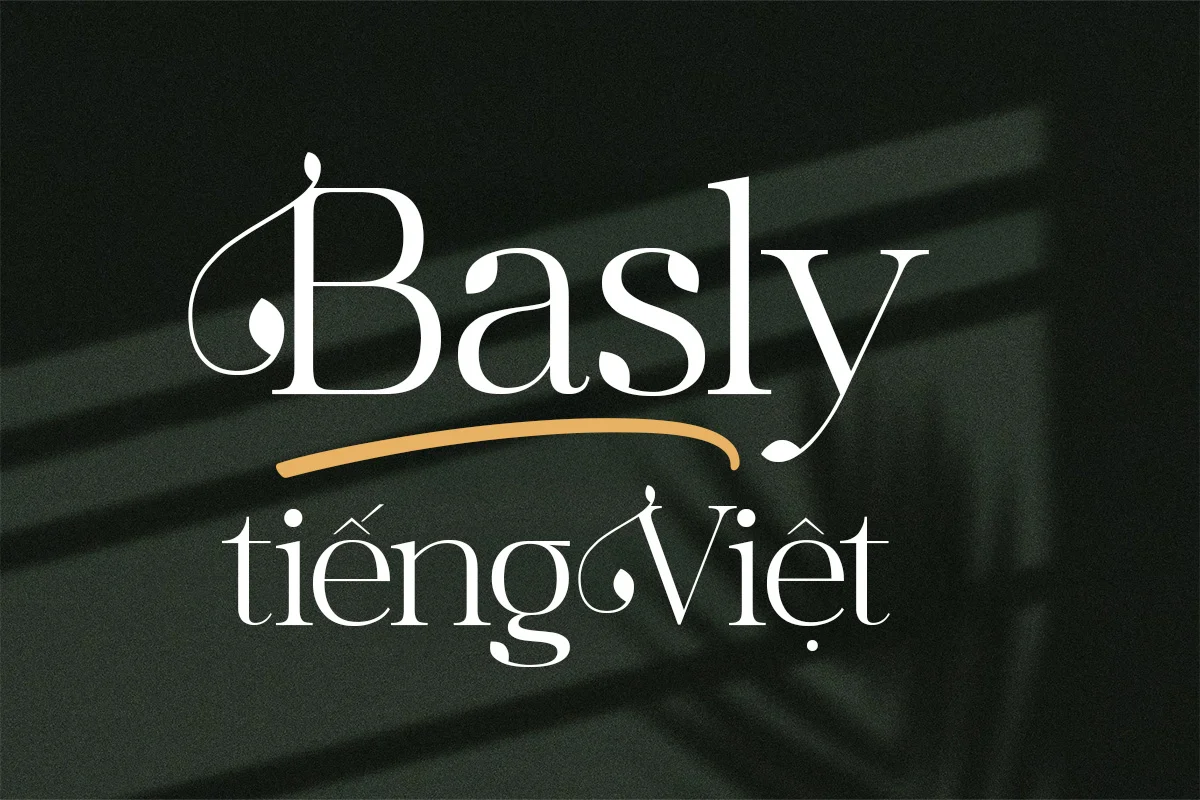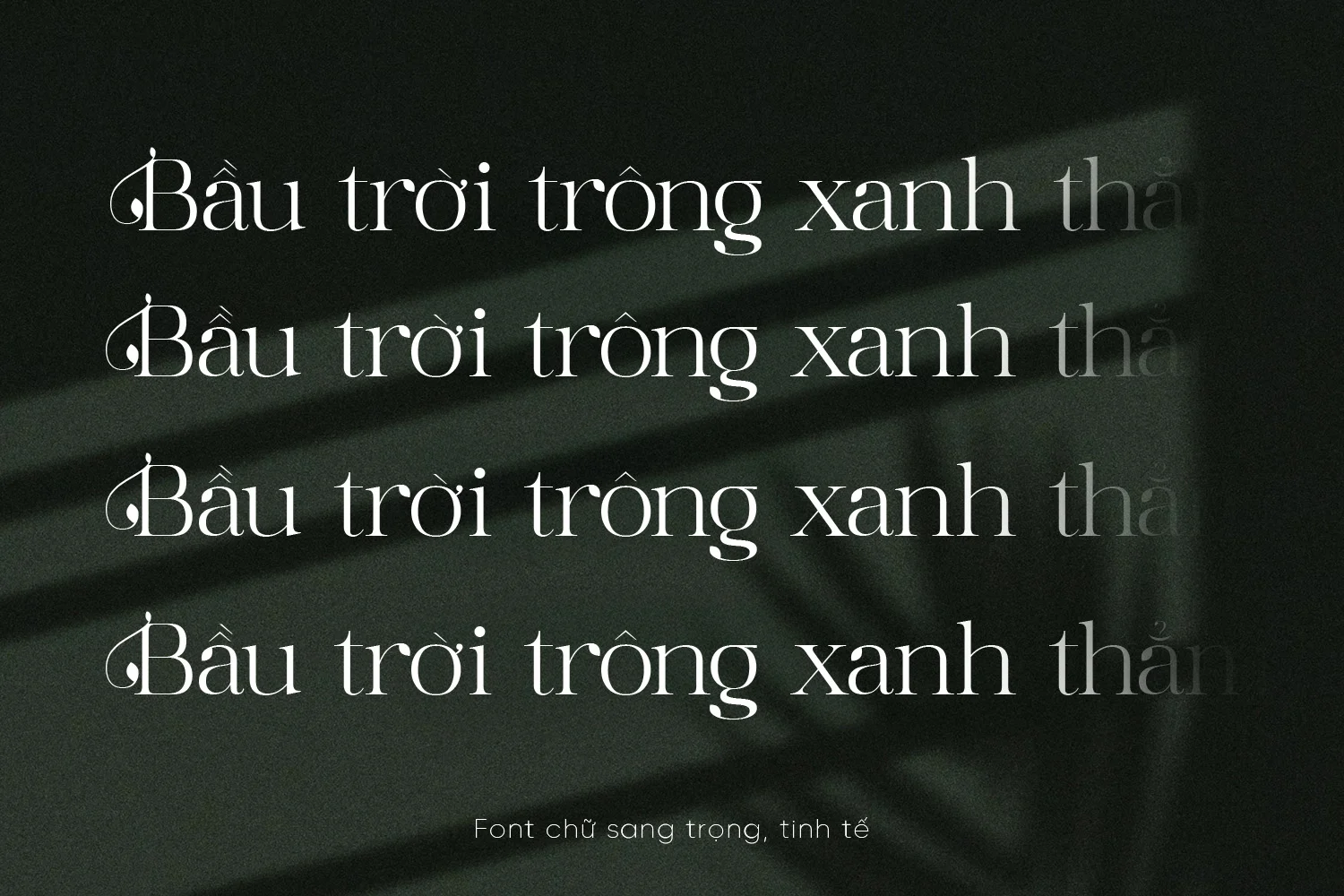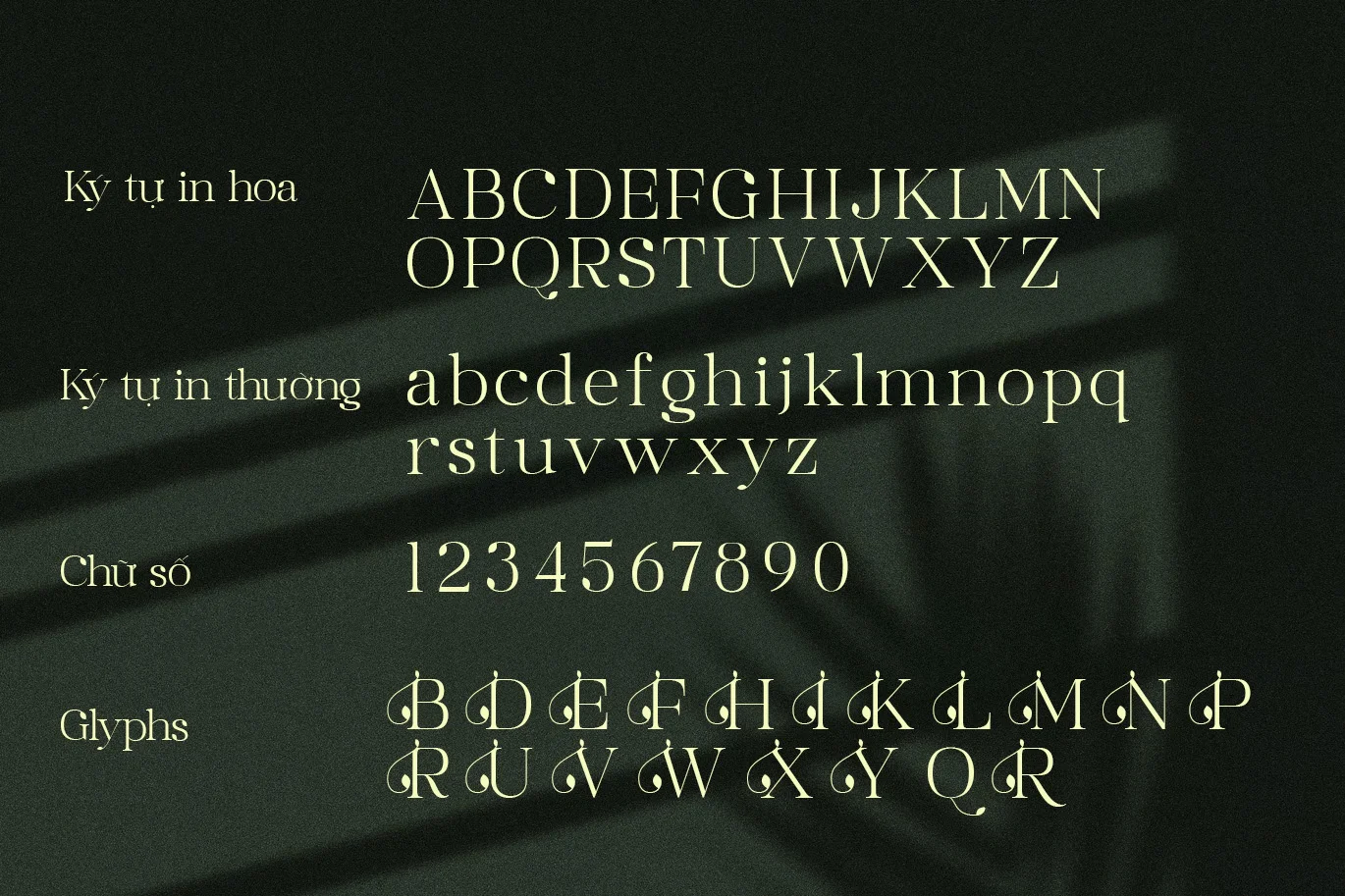
DVN Basly tiếng Việt - Font chữ tinh tế với hoa lá trang trí tuyệt đẹp
DVN Basly là một typeface serif mang hơi hướng hiện đại, nhấn nhá bằng các chi tiết bay bổng ở đầu và cuối chữ. Font Việt hóa này vừa mạnh mẽ, vừa mềm mại, giúp tôn lên tính thẩm mỹ sang trọng trong thiết kế. Phù hợp cho branding, tiêu đề tạp chí, bìa sách, mỹ phẩm và các dự án sáng tạo cần sự khác biệt.